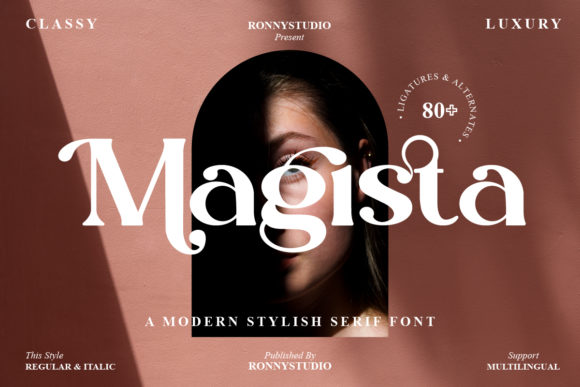
[Creativefabrica] Magista Font (2022)
Magista - это элСгантный ΠΈ ΡˆΠΈΠΊΠ°Ρ€Π½Ρ‹ΠΉ ΡˆΡ€ΠΈΡ„Ρ‚ с засСчками.
Π‘ΠΌΠ΅Π»ΠΎ добавляйтС Π΅Π³ΠΎ Π² свои ΠΏΡ€ΠΎΠ΅ΠΊΡ‚Ρ‹, ΠΈ Π²Ρ‹ Π±ΡƒΠ΄Π΅Ρ‚Π΅ Π² восторгС ΠΎΡ‚ Ρ€Π΅Π·ΡƒΠ»ΡŒΡ‚Π°Ρ‚ΠΎΠ².